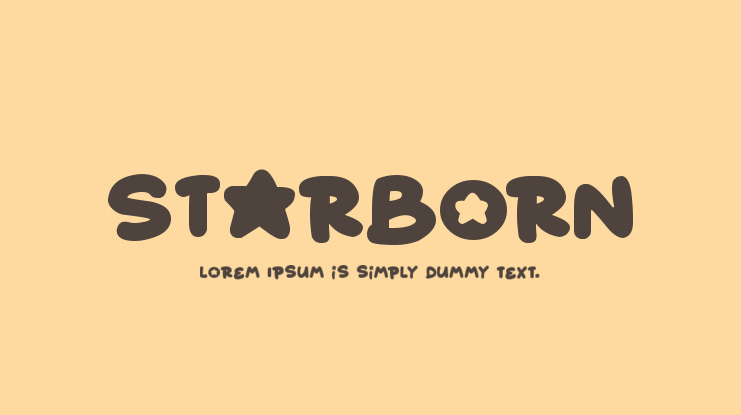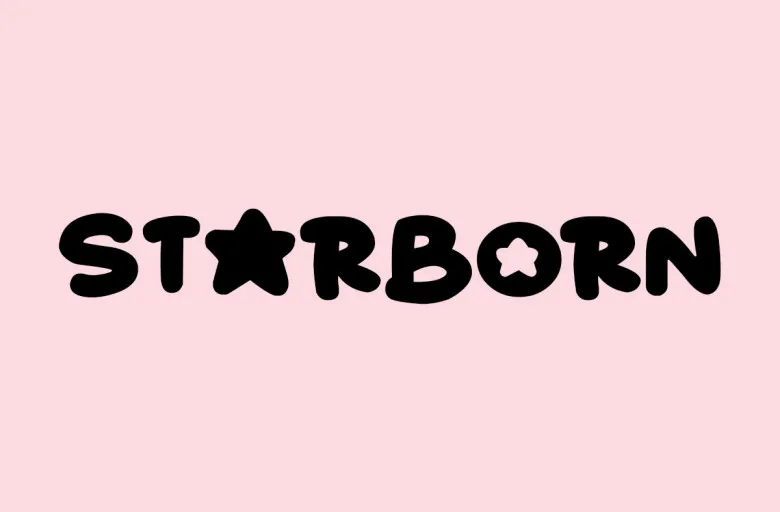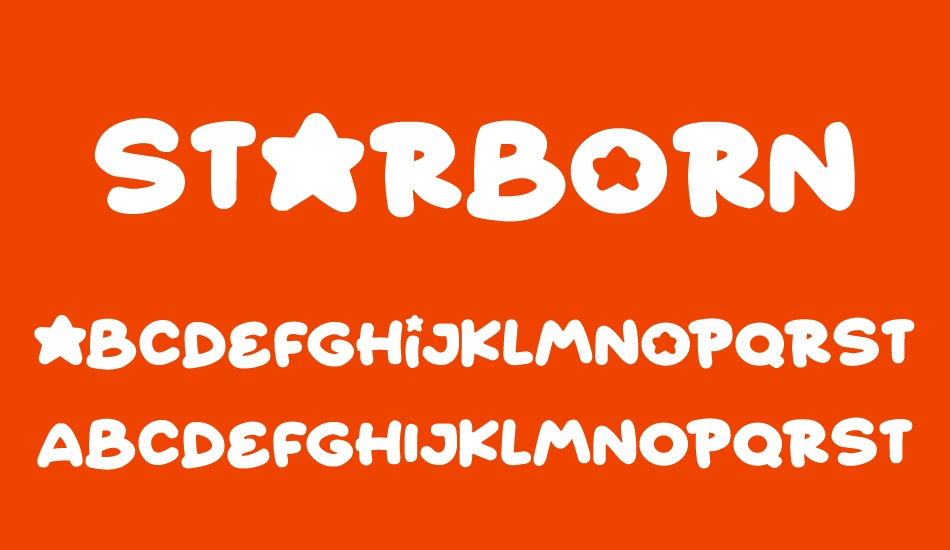
Starborn font Việt hóa là bộ phông chữ thuộc dòng Display nổi tiếng với thiết kế mập mạp, vui nhộn và vô cùng đáng yêu. Với cấu trúc chữ “Bubbly” (dạng bong bóng) đặc trưng, Starborn mang lại cảm giác thân thiện, năng động, cực kỳ phù hợp cho các thiết kế Logo game, poster sự kiện thiếu nhi hoặc bao bì ngành bánh kẹo. Doozypack.vn cung cấp link download font Starborn chuẩn, hỗ trợ đầy đủ tiếng Việt giúp bạn sở hữu bộ phông chữ chỉn chu để hiện thực hóa những ý tưởng thiết kế bắt mắt nhất mà không lo lỗi dấu thanh.
Đặc điểm thiết kế độc đáo của bộ font Starborn
Starborn không chỉ đơn thuần là một bộ chữ béo; nó sở hữu những đặc tính thị giác giúp bản thiết kế của bạn trở nên sinh động và có “hồn” hơn.
Mẫu chữ Starborn độc đáo
Phong cách thiết kế “Bubbly” vui nhộn và thân thiện
Đặc trưng lớn nhất của font Starborn là các đường nét được bo tròn tuyệt đối, mô phỏng hình dáng của những quả bóng hoặc những viên kẹo ngọt. Cấu trúc chữ này loại bỏ hoàn toàn sự khô cứng của các dòng phông chữ hình học truyền thống, tạo ra một không gian thiết kế đầy sự tích cực và dễ mến. Chính sự thân thiện này giúp thương hiệu của bạn dễ dàng kết nối với phân khúc khách hàng trẻ tuổi hoặc các bậc phụ huynh.
Cấu trúc chữ Bold mạnh mẽ và vững chãi
Dù mang phong cách đáng yêu, Starborn vẫn giữ được sự vững chắc nhờ độ dày nét (Weight) cực lớn. Mỗi ký tự khi đứng độc lập trông như một khối kiến trúc nhỏ, giúp tiêu đề trên bao bì luôn nổi bật hoàn toàn. Khi sử dụng bản starborn việt hóa chuẩn tại Doozypack.vn, hệ thống dấu thanh được tinh chỉnh mập mạp hài hòa với thân chữ, đảm bảo văn bản tiếng Việt luôn cân đối và đẹp mắt.
Thiết kế typography trẻ trung
Lời khuyên từ xưởng in: Vì Starborn có nét chữ khá dày, nếu bạn dự định in trên chất liệu giấy Kraft có độ thấm mực mạnh, hãy ưu tiên sử dụng bản OTF và tăng nhẹ khoảng cách giữa các chữ cái (Tracking) để tránh hiện tượng mực bị lan làm bít các khe chữ nhỏ như chữ ‘e’ hay ‘a’.
Mẫu chữ trên poster